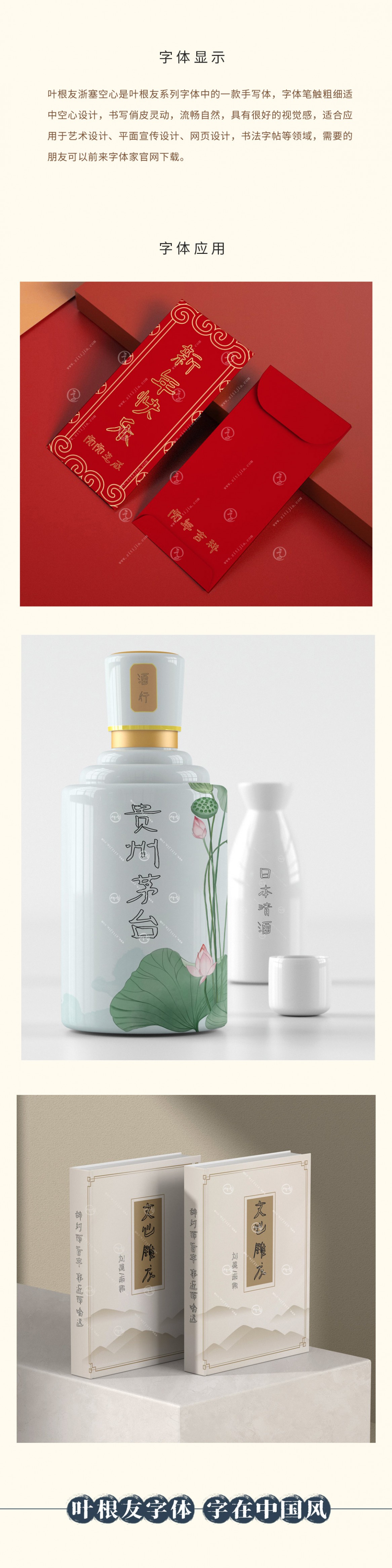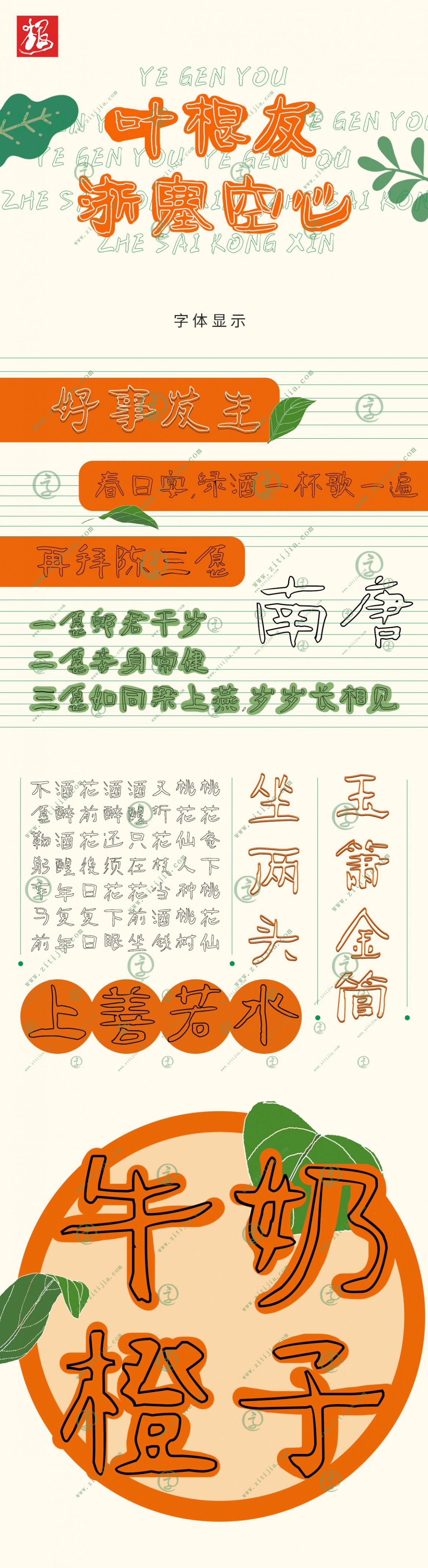
葉根友浙塞空心
葉根友浙塞空心是葉根友系列字體中的一款手寫(xiě)體,字體筆觸粗細(xì)適中空心設(shè)計(jì),書(shū)寫(xiě)俏皮靈動(dòng),流暢自然,具有很好的視覺(jué)感,適合應(yīng)用于藝術(shù)設(shè)計(jì)、平面宣傳設(shè)計(jì)、網(wǎng)頁(yè)設(shè)計(jì),書(shū)法字帖等領(lǐng)域,需要的朋友可以前來(lái)字體家官網(wǎng)下載。